Antes de nadada, queremos lanzar la pregunta: ¿Qué es el lettering en negativo? Pues bien, cuando una letra o un dibujo están en negativo significa que el fondo es o se pinta de colores y las letras o los dibujos quedan del color natural del soporte. Es una técnica que ya se utilizaba en las pinturas rupestres cuando la persona ponía su mano encima de la roca y soplaba el pigmento alrededor para que quedase, en negativo, la silueta de la mano. Aquí podéis ver un ejemplo:
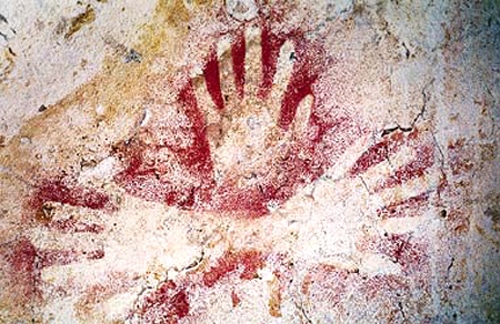
En lettering hay dos maneras de hacer lettering en negativo. Uno es utilizando un folio o cartulina de color y dibujando las letras en blanco, utilizando un bolígrafo de gel blanco, un lápiz blanco o una tinta blanca. Otra manera, la que os vamos a enseñar en este tutorial, es dibujando las letras dejando el interior blanco y rellenando los contornos y el fondo en negro u otro color.
Tutorial paso a paso de lettering en negativo
Ahora que ya sabemos lo que es el lettering en negativo, pasamos a explicaros el paso a paso para poder realizarlo de la segunda forma que os hemos explicado:
Paso 1
Lo primero es dibujar la letra con lápiz, ya sea estilo cursiva, como el que ponemos de ejemplo, ya sea mayúscula sin remates, con… lo que queráis.
Paso 2
Después hay que repasar los contornos con un puntafina o con un rotulador del color que queráis que tenga el fondo, así como los huecos que hay en las letras como la «a», la «e», la «g» o la «o». ¡Ojo! el punto de la «i» no se rellena, se repasa el contorno.
Paso 3
Se sigue rellenando el fondo con el color escogido, en este caso, el negro. Os mostramos también otras opciones de lettering en negativo con otros tipos de letra y con fondos de otros colores y otros estampados para que veáis que puede ser muy distinto el resultado (disculpad, no están muy bien hechos porque eran borradores).